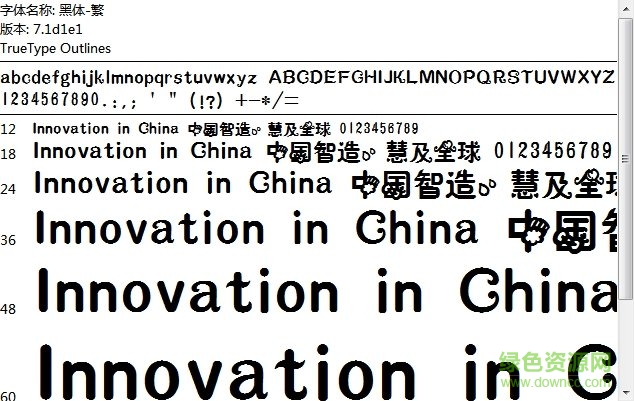
花花愛彩虹ttf字體是一款有歐哲花朵、愛心、水滴等多種裝修的卡通字體,整體十分Q萌活潑,支持日文、中文、韓文等多種輸入,給大家?guī)砀鄻踊倪x擇,綠色資源網(wǎng)今日推薦!
花花愛彩虹采用了花紋風(fēng)格,線條粗細(xì)適中,是一款適用于海報(bào)設(shè)計(jì)、廣告圖片設(shè)計(jì)等文字領(lǐng)域的藝術(shù)字體。字庫完整,能滿足大家的更多需要!
花花愛彩虹體有著非常多的可愛點(diǎn)綴,兼具pop字體和海報(bào)字體的特色,給人十分歡唱的視覺體驗(yàn),文字更加生動(dòng)有活力。